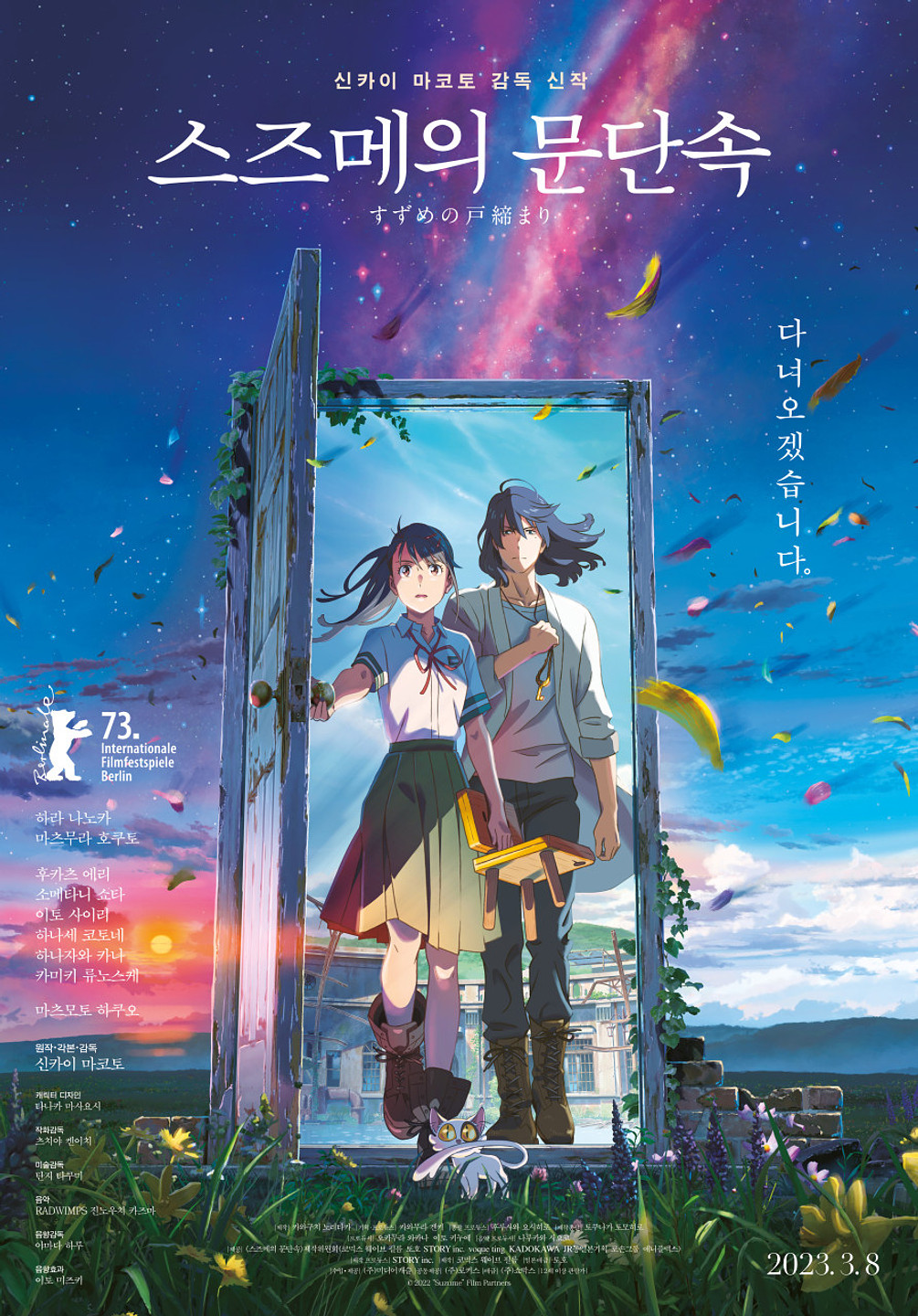
스즈메 포스터에서 저기 제못 써져있는 폰트가 뭘까요?? 어떤 답변을 보았을 떈 아리따부리라고 하신 것 같은데, 제목 글꼴이랑 다르게 모음부분이 휘어져있지가않아서요,, ㅠ 이런 경우에는 일러스트레이터와 같은 프로그램에서 휘어버린걸까용 아님 폰ㅌ크가 원래 저런건거요?? 혹시 아는 분 있으면 답변 주세요